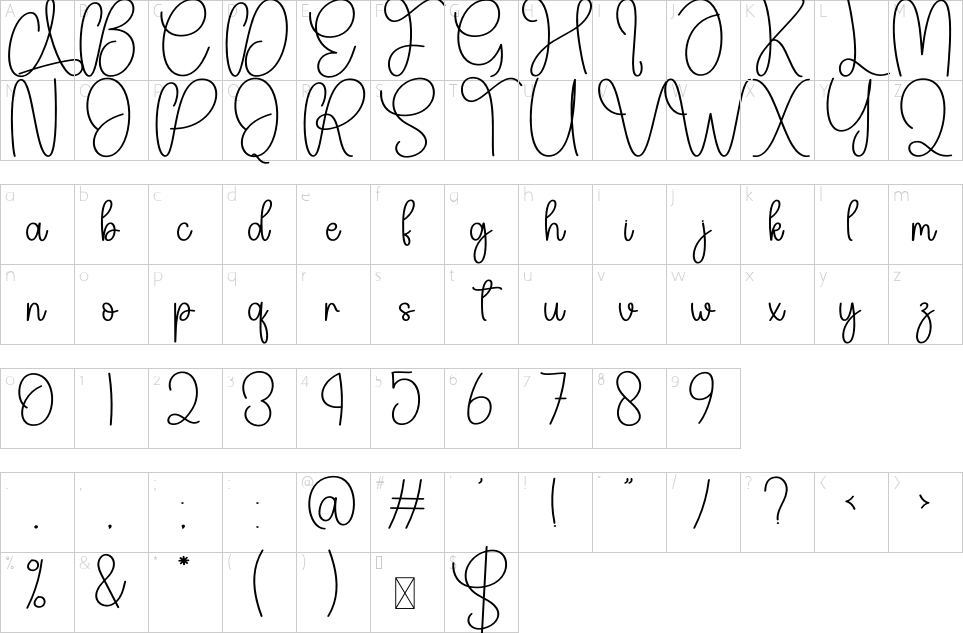
Descubra a essência da vida em Amsterdam Font, uma fonte única e vibrante projetada pelo designer scratchones. Esta fonte foi criada para oferecer um toque de sofisticação e modernidade para seus projetos digitais. Com um design elegante e detalhado, Amsterdam Font é perfeito para uso em aplicativos de Windows e Mac, trazendo um ar de frescor a qualquer projeto. Sua versão gratuita permite que designers e criativos de todo o mundo achem facilmente o estilo que procuram para seus projetos de design. Com um design minimalista e sofisticado, esta fonte é um excelente complemento para trabalhos corporativos, websites e materiais de marketing. Se você está procurando por uma fonte que combine estilo com facilidade de uso, Amsterdam Font é uma ótima escolha. Descubra hoje mesmo e traga a Amsterdam Spirit para seus projetos.